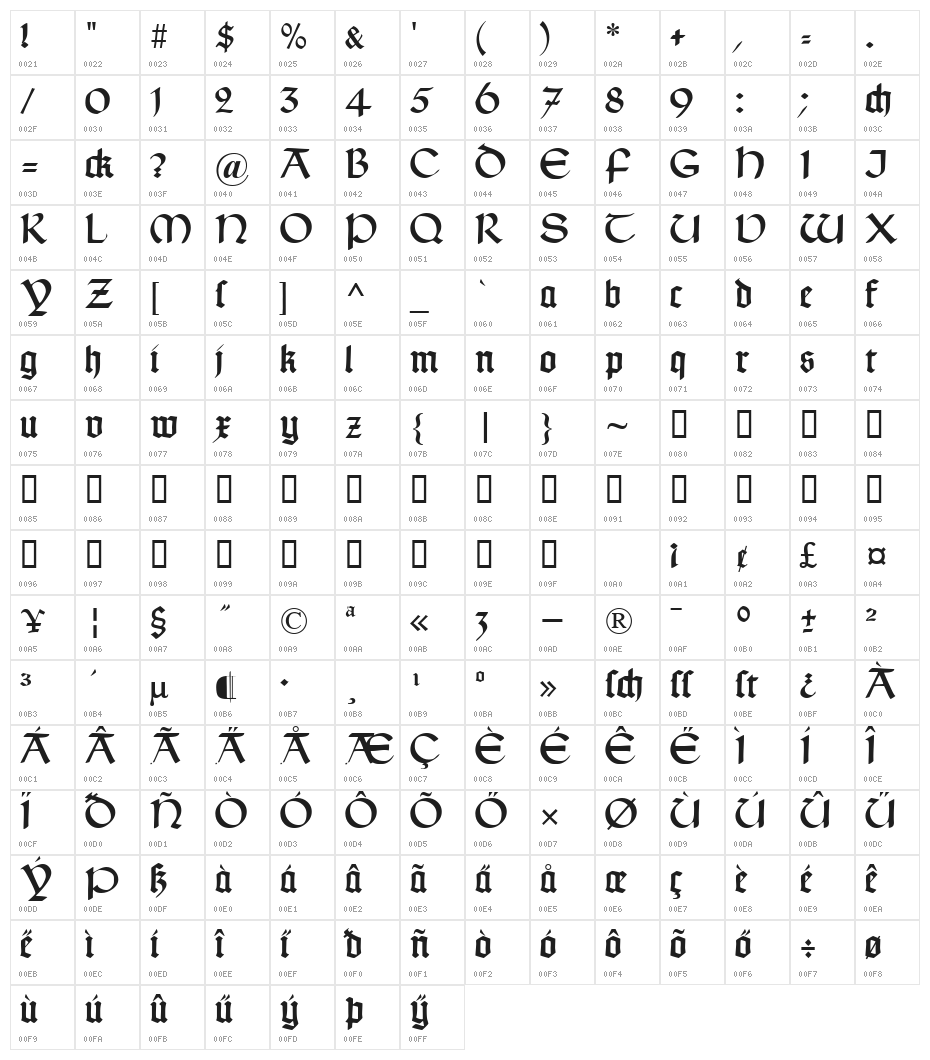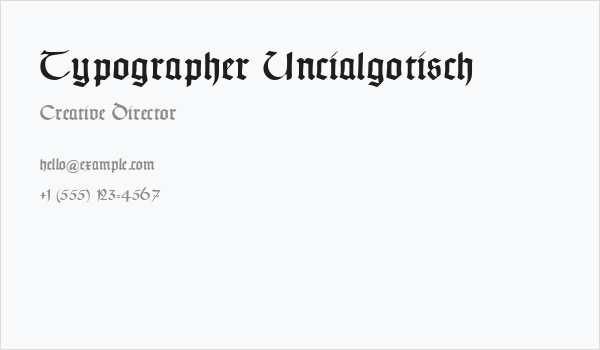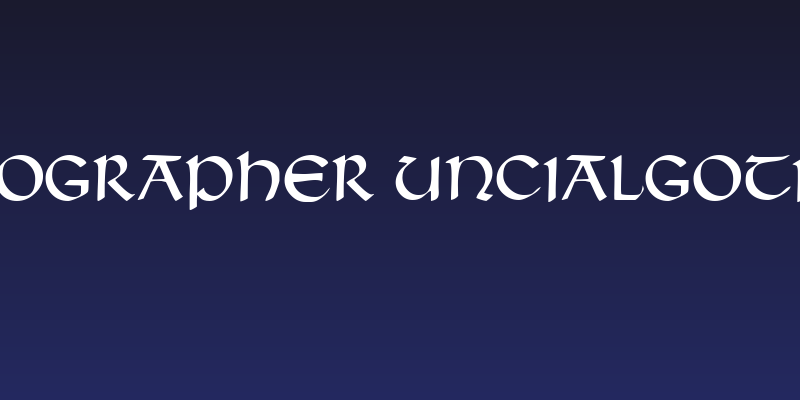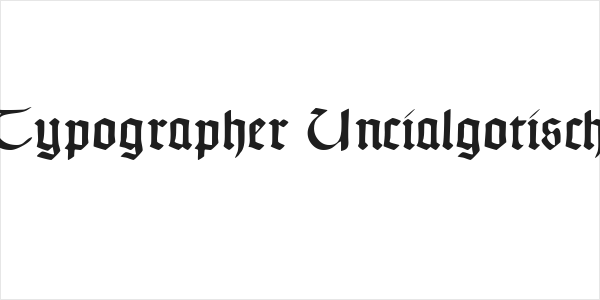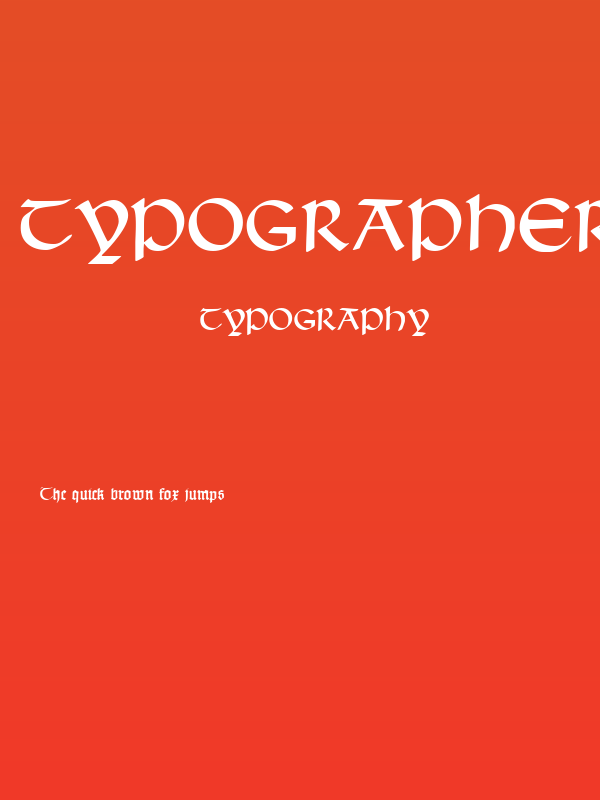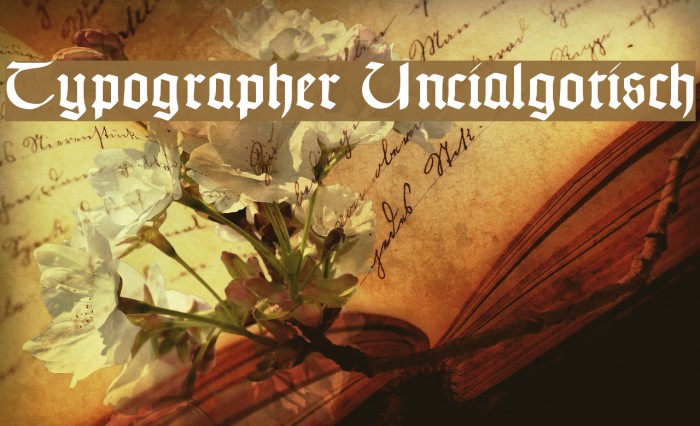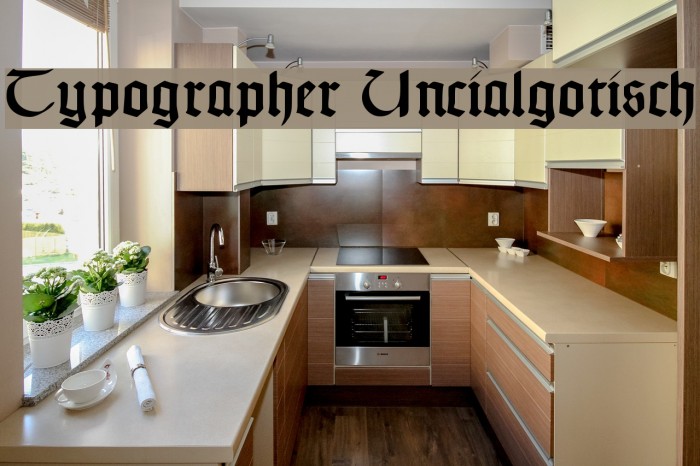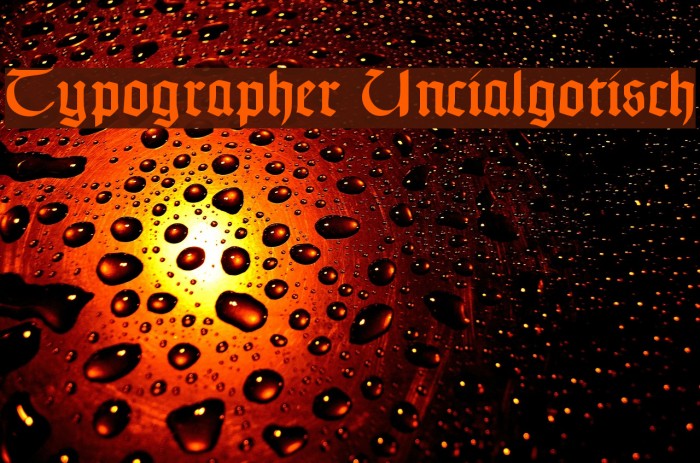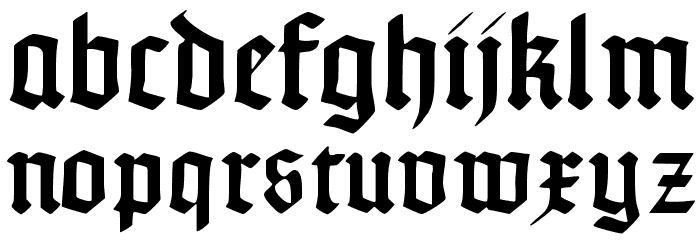
Typographer Uncialgotisch Font
✎ Gothic
| Stile generale | Gothic, Medieval |
| Caso d'uso | Headlines, Logos, Decorative text |
| Progetti proposti | Ideal for historical documents, fantasy book covers, themed event invitations, and branding that requires a gothic or medieval aesthetic. |